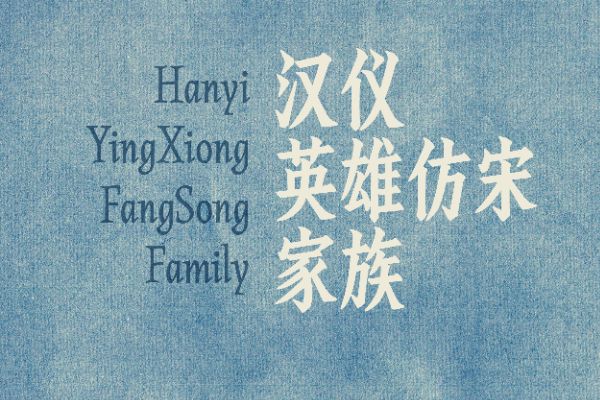
汉仪英雄仿宋 85U
英姿雄健,端正挺拔,气度非凡。以仿宋体作为基础,字形窄长而略有倾斜,笔画铿锵有力而又书写韵味,细节精致考究。英雄不器,包含6种字重的汉仪英雄仿宋家族可以满足从标题到正文的全面排版需求,既有仿宋体的书卷气质,又多了力量感,文武双全,适合用于书籍展览等文化艺术领域,也适用于各类产品的包装及广告以提升格调,在传统节庆的使用场景中独具特色,是为全才英雄。